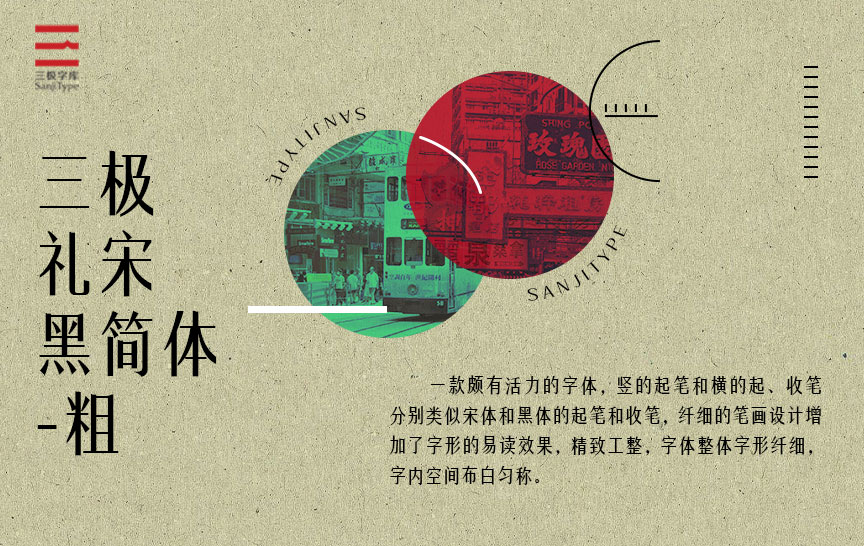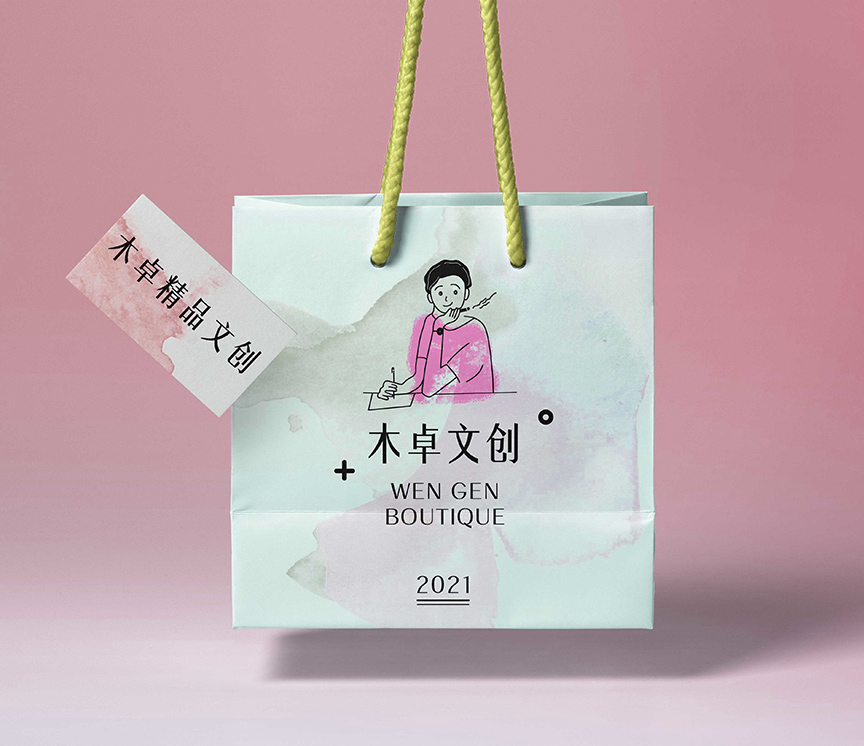
三极礼宋黑简体-粗
王荣诚
混合字体
三极礼宋黑简体是一款颇有活力的字体,竖的起笔和横的起、收笔分别类似宋体和黑体的起笔和收笔,纤细的笔画设计增加了字形的易读效果,精致工整,字体整体字形纤细,字内空间布白匀称。适用于书刊的标题和商业类品牌的广告语设计、商业产品的包装设计。
适用媒介:杂志、书籍、广告语、标志、宣传册、包装、影视、动漫、交互设计。